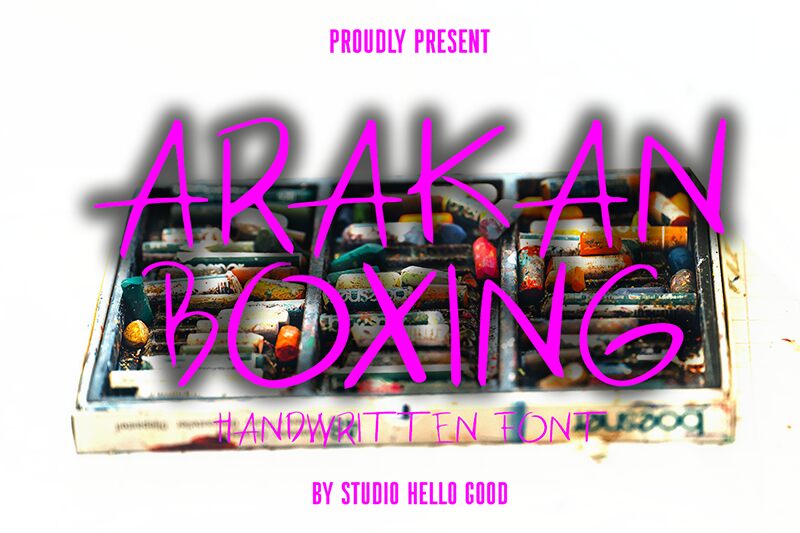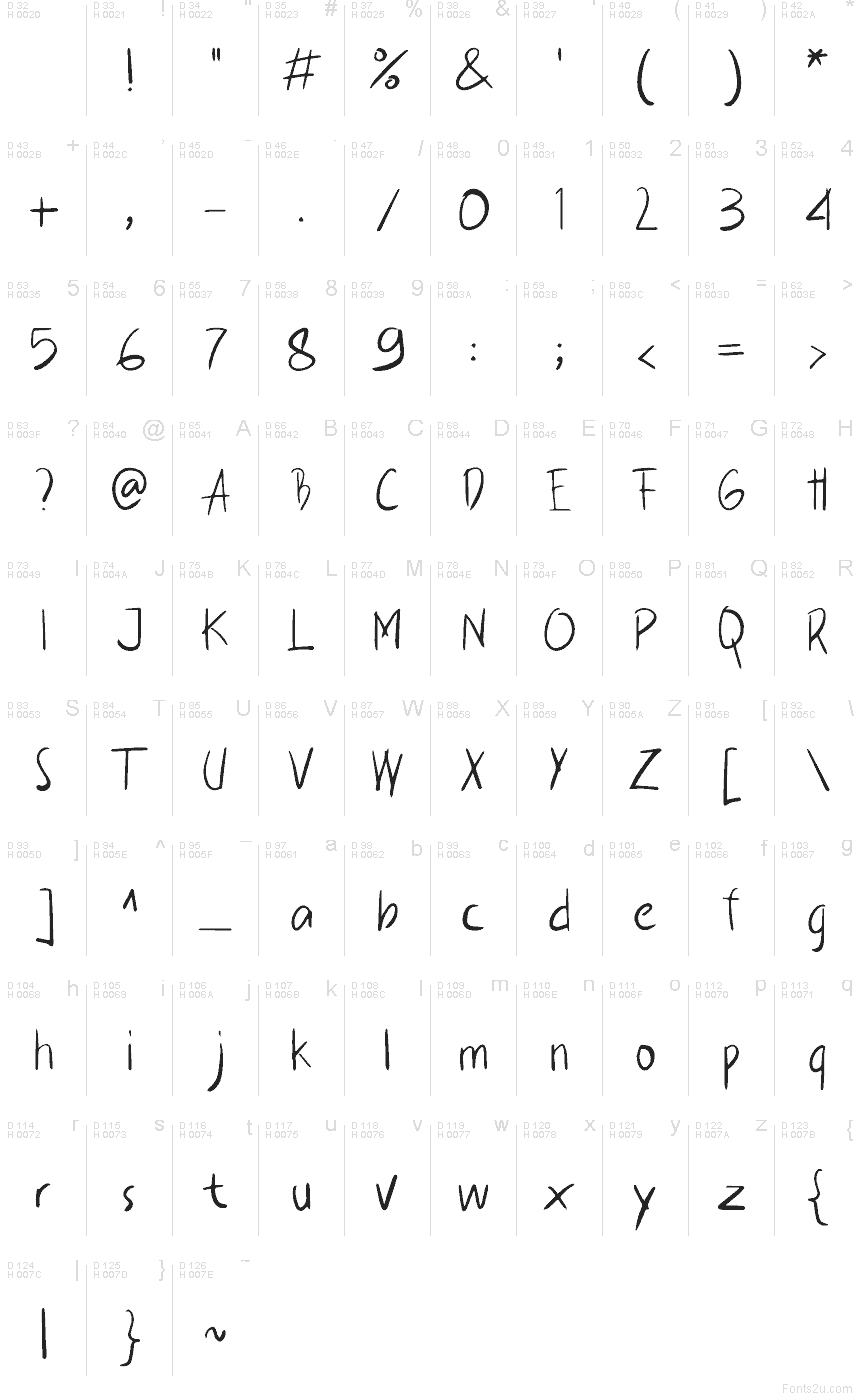
Arakan Boxing
Arakan Boxing — це безкоштовний рукописний шрифт із довгими, вільними штрихами та динамічним, злегка нерівномірним ритмом, що створює враження письма одним безперервним рухом. Поєднання гострих кутів і відкритих кривих надає літерам живого, індивідуального характеру, позбавленого зайвої відшліфованості.
Arakan Boxing чудово підходить для логотипів, запрошень, заголовків на постерах, графіки для соціальних мереж та упаковки, де потрібен ефект рукописної замітки. Цей безкоштовний шрифт додає безпосередності та ескізності коротким текстам, що робить його ідеальним вибором для брендингу та редакційних акцентів із неформальним, живим звучанням.
Studio Hello Good
Rachmad Bagus Fatchi